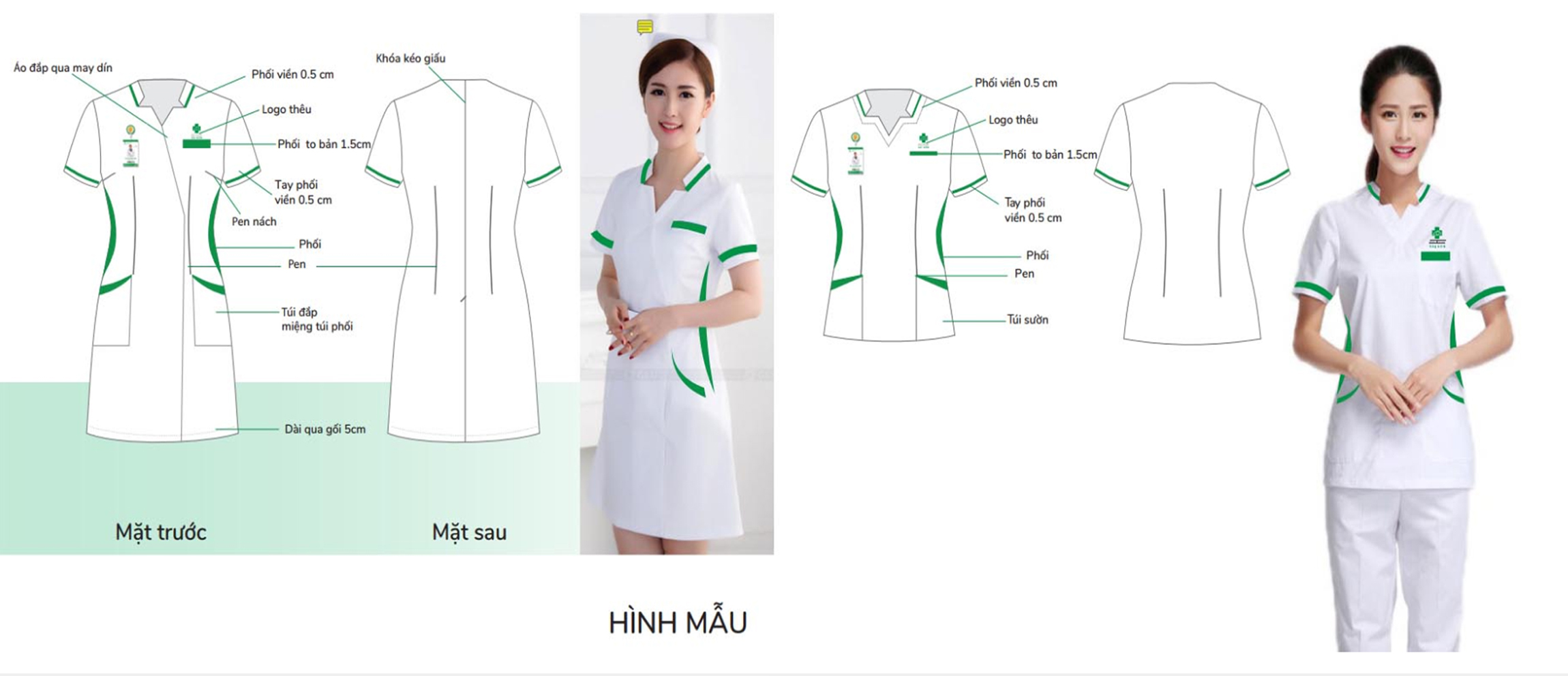
Một bác sĩ vừa nhận bộ blouse mới, kèm dòng chức danh BS.CKII thêu trên ngực trái. Tuy nhiên, khi đứng cách vài mét, nét chỉ mỏng manh ấy gần như biến mất, khiến dòng chữ trở nên mờ nhạt. Cảm giác trang trọng của khoảnh khắc phong tặng tan biến, thay vào đó là một vệt màu khó phân biệt trên nền vải trắng. Sự cố này không xuất phát từ chất lượng vải hay kỹ thuật may, mà nằm ở việc lựa chọn font thêu áo blouse ban đầu.
Font chữ thêu áo blouse: 3 sai lầm khiến chữ chức danh mất uy tín
Một dòng chữ nhỏ trên ngực trái có thể tạo nên khác biệt lớn trong ấn tượng đầu tiên. Việc lựa chọn font không đúng kỹ thuật thường vô tình phá hỏng tính trang trọng của đồng phục y tế. Dưới đây là ba lỗi phổ biến cần tránh khi thực hiện thêu tên bác sĩ và chức danh.
Lỗi 1: Chọn font quá mảnh
Nhiều nhà thiết kế ưu tiên sự nhẹ nhàng, dẫn đến việc chọn các dòng chữ thin hoặc light. Thực tế, khi nét chữ mỏng hơn 1mm, chi tiết sẽ bị mất đi sau khi thêu, đặc biệt trên nền vải trắng có độ phản chiếu cao. Nét chỉ không đủ độ phủ để giữ hình dạng gốc, khiến dòng chữ trở nên mờ nhòe và khó nhận diện khi quan sát từ xa.
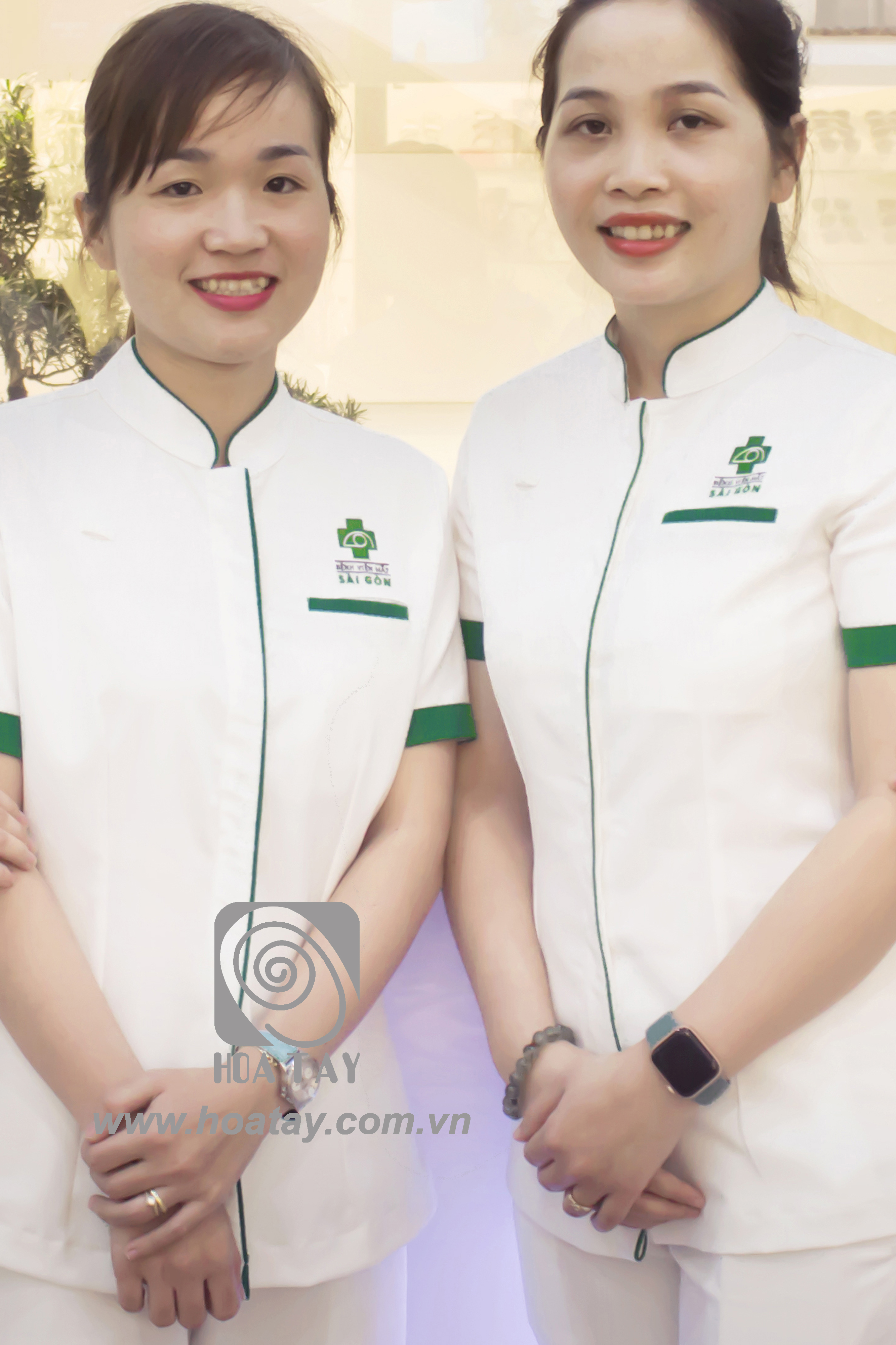
Lỗi 2: Sử dụng font trang trí cầu kỳ
Các dòng chữ script hoặc decorative với nhiều nét cong và hoa văn tạo vẻ thẩm mỹ trên in ấn nhưng thất bại trên vải. Khi nhìn từ khoảng cách 2-3m, các nét phức tạp này gộp lại thành một vệt màu không thể đọc. Sự phức tạp của font chữ trang trí không tương thích với yêu cầu về tính rõ ràng và sự trang trọng cần có của chức danh y tế.
Lỗi 3: Kết hợp quá nhiều loại font
Việc dùng ba kiểu chữ khác nhau cho tên, chức danh và phòng ban trong cùng một cụm thêu tạo cảm giác rối mắt. Cách phối hợp này làm đồng phục trông giống áp phích quảng cáo hơn là trang phục chuyên môn. Sự đơn giản và nhất quán về kiểu chữ giúp người nhìn dễ dàng phân tách thông tin, giữ được sự thanh lịch vốn có của blouse y tế.
Giải thích kỹ thuật: Giới hạn của máy thêu
Máy thêu vi tính hoạt động dựa trên các mũi chỉ rời rạc, không liên tục như đường in. Khi file thiết kế có nét quá mảnh, máy không thể tái hiện đúng tỷ lệ do giới hạn độ phân giải của kim. Hiện tượng “mờ” xảy ra khi chỉ thêu không thể lấp đầy đủ khoảng không gian nhỏ giữa các nét, dẫn đến thiếu chi tiết trên thành phẩm. Hiểu rõ đặc điểm vật lý của quá trình thêu giúp người quản lý đưa ra quyết định thiết kế chính xác hơn, tránh những sai sót gây tổn hại đến hình ảnh thương hiệu.
Chọn font chữ thêu đẹp: Tiêu chuẩn kỹ thuật cho chức danh y tế
Khi quyết định font thêu áo blouse, yếu tố đầu tiên cần xem xét là kiểu chữ. Các phông sans-serif như Arial hay Helvetica, cùng với các phông serif có nét rõ ràng như Times New Roman hoặc Georgia, là lựa chọn tối ưu. Độ đậm nên ở mức Regular hoặc Bold để đảm bảo các đường nét không bị biến dạng sau khi thêu.
Bản vẽ kỹ thuật trên minh họa chi tiết vị trí logo và phom dáng áo blouse, nhấn mạnh tầm quan trọng của việc chuẩn hóa thông số ngay từ khâu thiết kế. Việc xác định đúng tỷ lệ và vị trí giúp đường thêu nằm cân đối trên nền vải, tránh cảm giác lạc lõng hay quá tải thị giác cho người đối diện.
Kích thước và khoảng cách đọc
Tính đọc được của chữ thêu phụ thuộc trực tiếp vào kích thước ký tự. Tiêu chuẩn chung là chữ cao từ 8 đến 10mm, cho phép nhận diện rõ ràng từ khoảng cách 2m. Với các chức danh cao như PGS.TS hay BS.CKII, chúng ta nên tăng kích thước lên 10-12mm. Điều này không chỉ giúp chữ dễ đọc hơn mà còn thể hiện sự tôn trọng phù hợp với cấp bậc chuyên môn của người mặc. Sự chênh lệch kích thước giữa tên và chức danh cũng cần được cân nhắc để tạo ra một hệ thống phân cấp thị giác rõ ràng, nơi chức danh được đặt bên dưới tên với font nhỏ hơn 1-2mm.
Màu sắc và sự tinh tế trong phối hợp
Màu chỉ thêu đóng vai trò then chốt trong việc tạo độ tương phản trên nền vải trắng. Xanh navy và xám đậm là những lựa chọn an toàn, tạo sự chuyên nghiệp mà không gây chói mắt. Chúng ta nên tránh các tông màu pastel hoặc những màu quá gần với màu áo, vì chúng sẽ khiến dòng chữ chức danh trở nên mờ nhạt và thiếu trọng tâm. Về số lượng màu, hãy giới hạn ở không quá hai màu trong cùng một cụm thêu bao gồm tên và chức danh. Nếu có sự hiện diện của logo đối tác, việc chuyển sang thêu đơn sắc (monochrome) là một giải pháp thông minh để giữ gìn sự tinh tế và tránh cảm giác trang phục biến thành áp phích quảng cáo.
Cuối cùng, hãy nhớ rằng sự trang trọng không đến từ việc thêu nhiều thông tin nhất có thể, mà từ sự gọn gàng và chuẩn xác trong từng chi tiết nhỏ. Một mẫu thêu đạt chuẩn là khi người nhìn có thể phân tách rõ ràng tên, chức danh và logo mà không cần phải đưa mắt lại gần để đọc.
Mẫu thêu áo blouse: Bố cục và khoảng trắng quyết định sự sang trọng
Trên một chiếc áo blouse trắng, khoảng trống giữa tên và logo có thể quan trọng không kém bản thân dòng chữ. Khi các thành phần thêu nằm quá gần nhau, mắt người nhìn khó phân tách thông tin, và cảm giác trang trọng biến thành sự bừa bộn.
Vị trí chuẩn và tỷ lệ cân bằng
Vị trí ngực trái là điểm chuẩn mực cho việc thêu tên và chức danh. Để giữ được vẻ chỉn chu, cụm thêu cần cách mép áo tối thiểu 1,5 cm và cách đường may hoặc túi áo tối thiểu 1 cm. Khoảng cách này giúp đường kim mũi chỉ không bị áp sát vào các chi tiết may, đảm bảo độ bền và thẩm mỹ khi áo được giặt công nghiệp nhiều lần.
Trong lần tới khi duyệt mẫu thêu, chúng ta có thực sự kiểm tra kỹ khoảng cách giữa tên và chức danh, hay chỉ dừng lại ở việc nhìn vào tổng thể từ xa? Câu hỏi này nhắc nhở rằng sự chỉn chu nằm ở những chi tiết mà người đọc thường bỏ qua, nhưng lại là yếu tố then chốt tạo nên sự khác biệt giữa một bộ đồng phục thông thường và một giải pháp đồng phục mang bản sắc riêng. Nếu bạn cần tư vấn thêm về các tiêu chuẩn thêu cho đồng phục y tế, đừng ngần ngại liên hệ để nhận lời khuyên phù hợp nhất với nhu cầu của cơ sở mình.